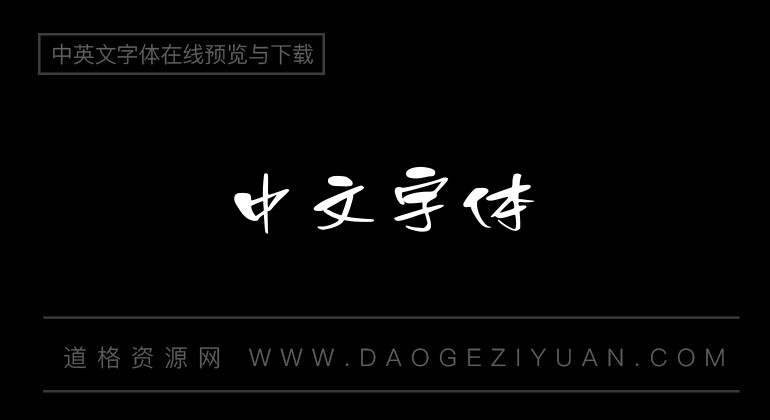
Aa小辣椒是一款由腾讯字体团队开发的中文字体,它采用了极简的风格,字体的线条细腻流畅,笔画精致,拥有清新的视觉效果,可以很好的支持网页和桌面设计。它有着极具特色的西文字母,让整体设计更加灵动,让文字更加生动活泼,可以满足多种设计需求。文件名:AaXiaoLaJiao-2.ttf
Aa小辣椒是一款非常不错的手写艺术字体,具有很好的视觉感,适合于文化类的宣传设计、商业类品牌的广告和产品包装设计以及个性化文字排版等较多场景。